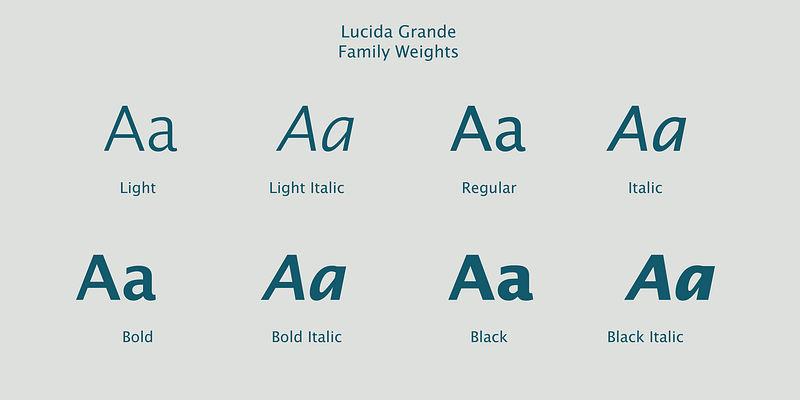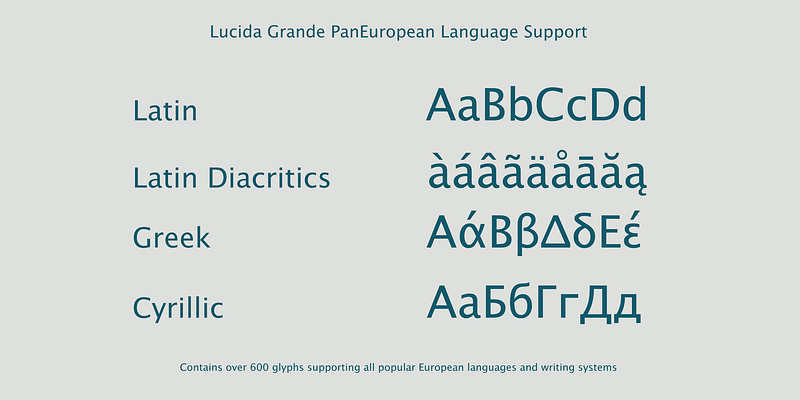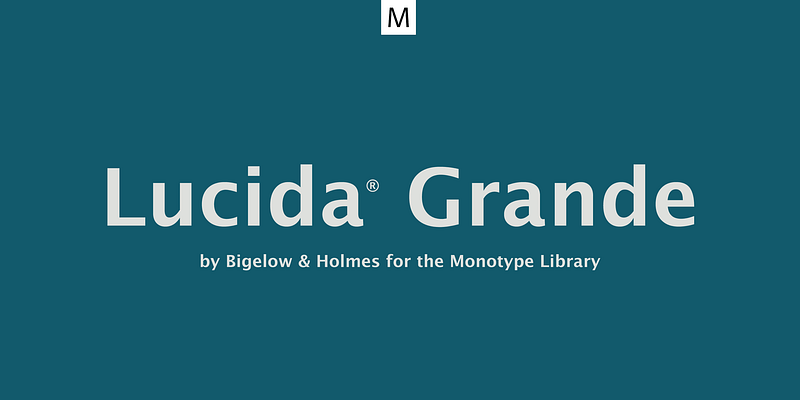
Lucida Grande est une police humaniste sans empattement, qui se caractérise par une grande hauteur d’œil, des lettres claires et un faible encombrement. Sa lisibilité optimale la rend lisible à l’impression et à l’écran, même en petite taille. Lucida Grande fait partie de la superfamille de polices Lucida de Bigelow & Holmes. Lucida est réputée pour sa lisibilité et sa vaste gamme de styles typographiques. La famille Lucida Grande comprend huit polices avec des épaisseurs allant de « Thin » à « Black », avec italique correspondante. Chaque police comporte 674 glyphes et prend en charge le jeu de caractères W1G. Ce jeu comprend les alphabets latin, grec et cyrillique, ce qui permet de prendre en charge de nombreuses langues d’Europe, d’Amérique et du monde entier.